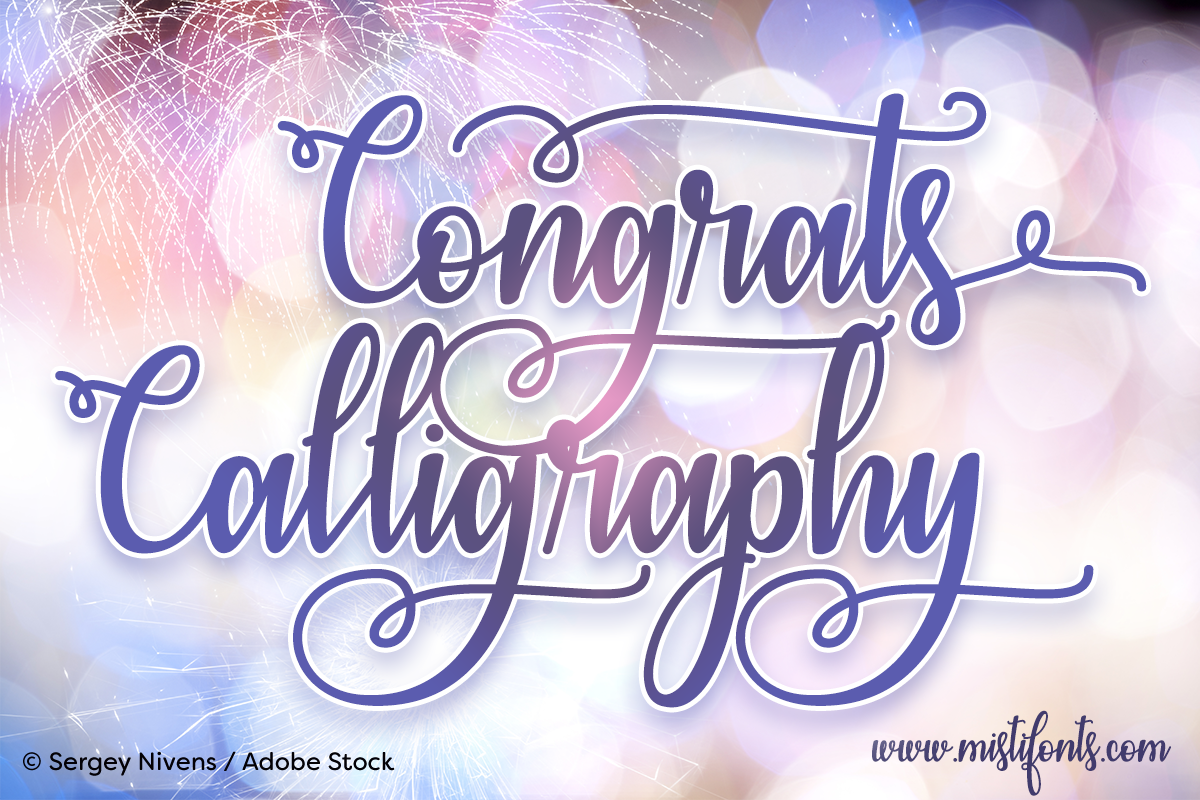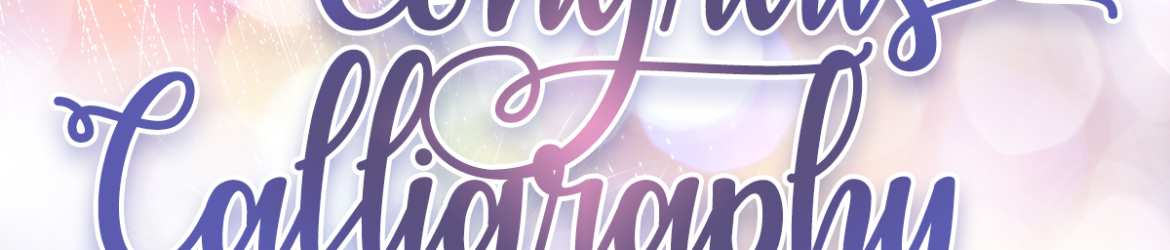
Introduzimos a Congrats Calligraphy Font! Esta elegante fonte foi criada pelo designer Misti’s Fonts, com a proposta de ser perfeita para combinar e permitir criar escrita a mão impecavelmente rápida e fácil. Desenhada especialmente para logos, frases escritas à mão, embalagens de produtos, cabeçalhos, cartazes, materiais promocionais, mídia social e cartões de felicitações. Ideal para quem quer dar um toque personalizado a seus projetos visuais, seja em impressão ou digital. Combinar essa fonte com outros elementos gráficos pode criar uma grande variedade de designs únicos e impecavelmente profissionais.